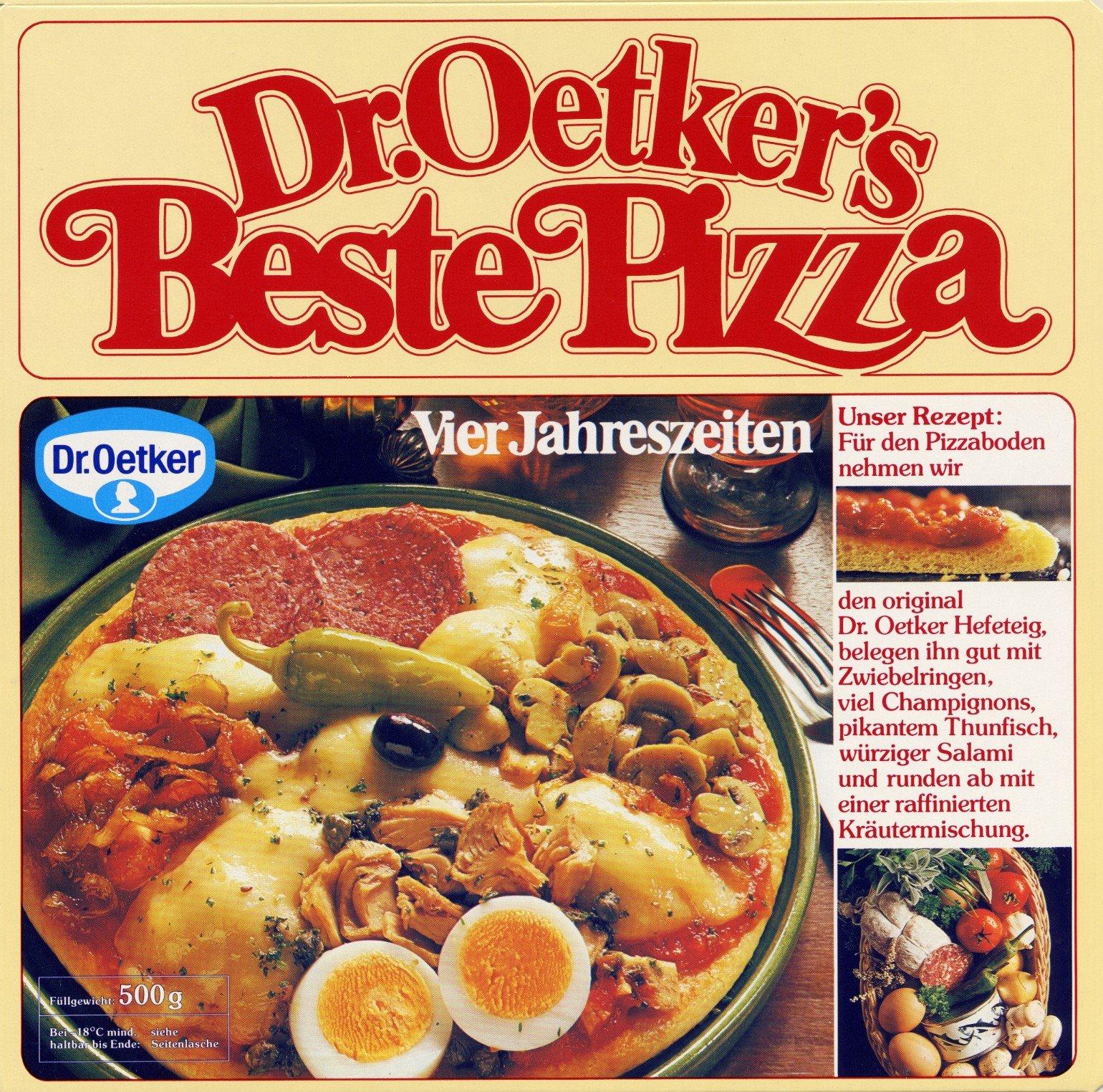
Suche diesen Font einer alten Pizza-Werbung (Dr. Oetker’s Beste Pizza)
freue mich über Hinweise zu dieser älteren Werbung von Dr. Oetker (es geht um die Überschrift). Darf auch etwas kosten.
Sieht mir fast nach einer grafisch verschönerten Clarendon oder Bookman aus - obwohl ich mir sicher bin, dass ich die Schnörkel von B und P auch schon in irgendeiner Schrift gesehen hab. der Text im roten Kasten müsste die Souvenir sein.